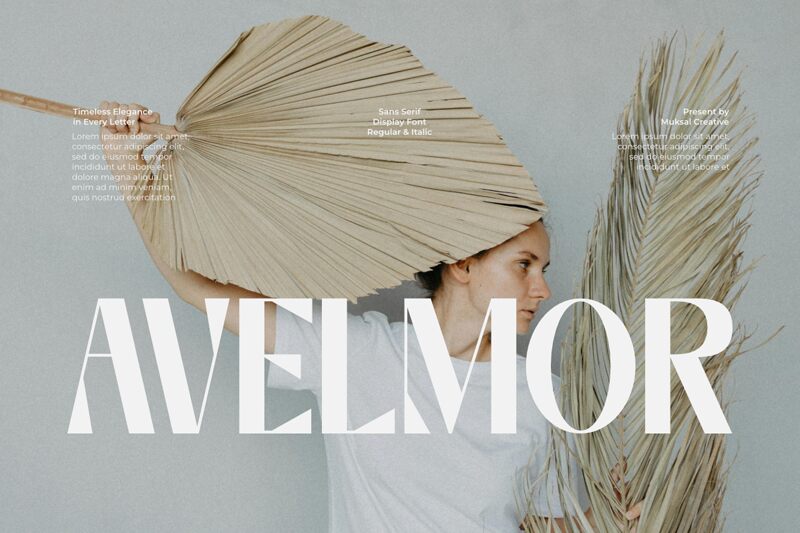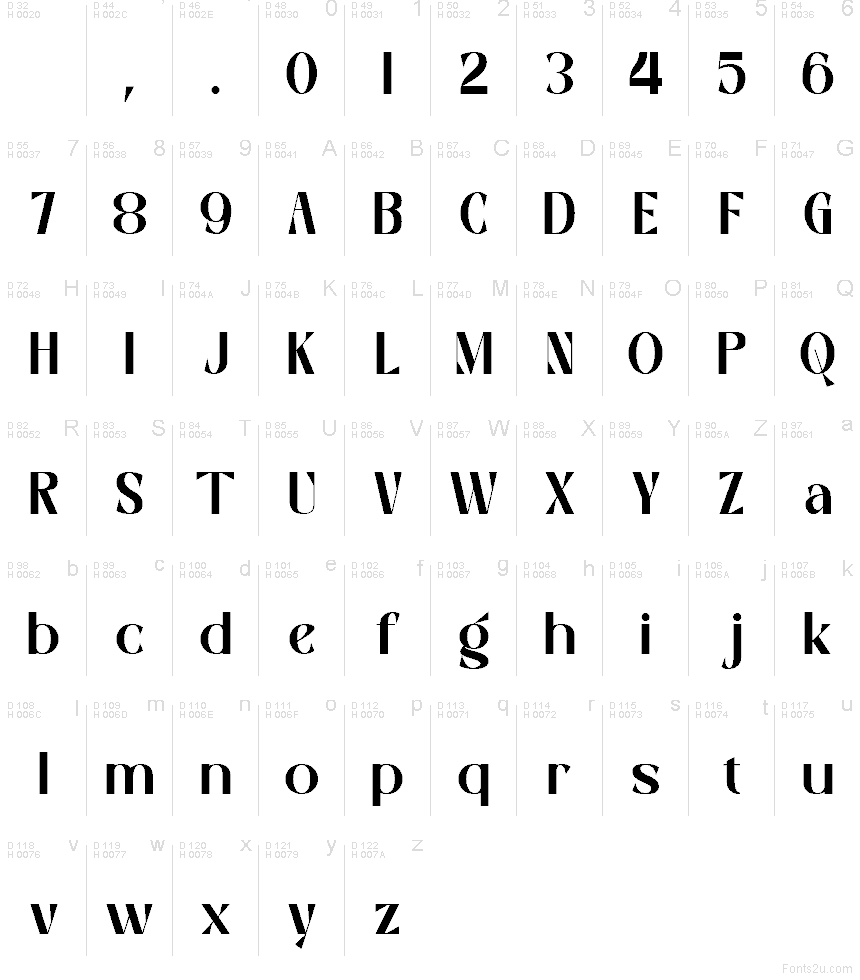
Avelmor، خط عرض (display) ريترو مجاني من تصميم Muksal Creative، يتميز بطابع طويل يشبه ملصقات الموضة الكلاسيكية، حيث تخلق الوصلات الدقيقة والسكتات السوداء العريضة إيقاعاً حاداً ومميزاً. هذا التباين يمنح التصميم نكهة تحريرية راقية من حقبة السبعينيات، دون أن يفقد حدته الدرامية والرسمية الطفيفة.
يُعد هذا الخط مثالياً لعناوين المجلات، وتغليف المنتجات الفاخرة، وهوية المطاعم، وأغلفة الألبومات، وعناوين الدعوات، حيث يحول الكلمات القصيرة إلى بيان بصري واضح. وتساعد خطوطه الرفيعة ومحوره الرأسي القوي في تأطير الشعارات وتصاميم منصات التواصل الاجتماعي التي تتطلب لمسة زخرفية ولكن متزنة في الوقت ذاته.